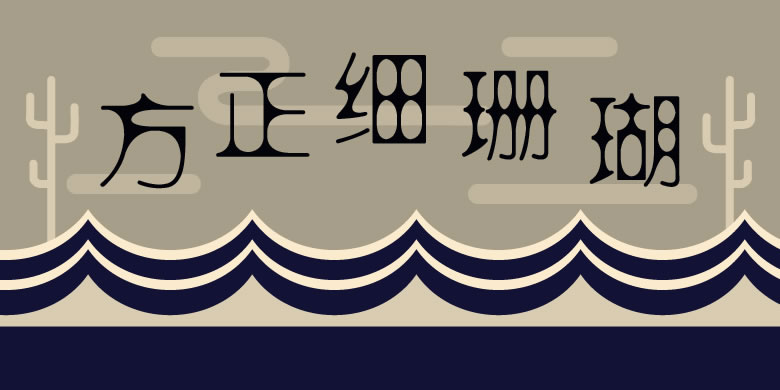
品牌:方正字库设计师:倪初万发行时间:2000字库编码:大陆简体(GB2312-80)、大陆繁体(GB12345-90)、简繁扩展(GBK)、港台地区(BIG-5)分类:创意字体
方正细珊瑚的设计以细圆体为基础,字形结构方正,笔画圆润且粗细均匀。这款字体最大的特征是笔画交叉处的内侧添加了圆角,彼此相融,似珊瑚生长的形态。方正细珊瑚的风格朦胧柔美,让人感觉轻松休闲,适用于品牌广告和产品包装的设计。